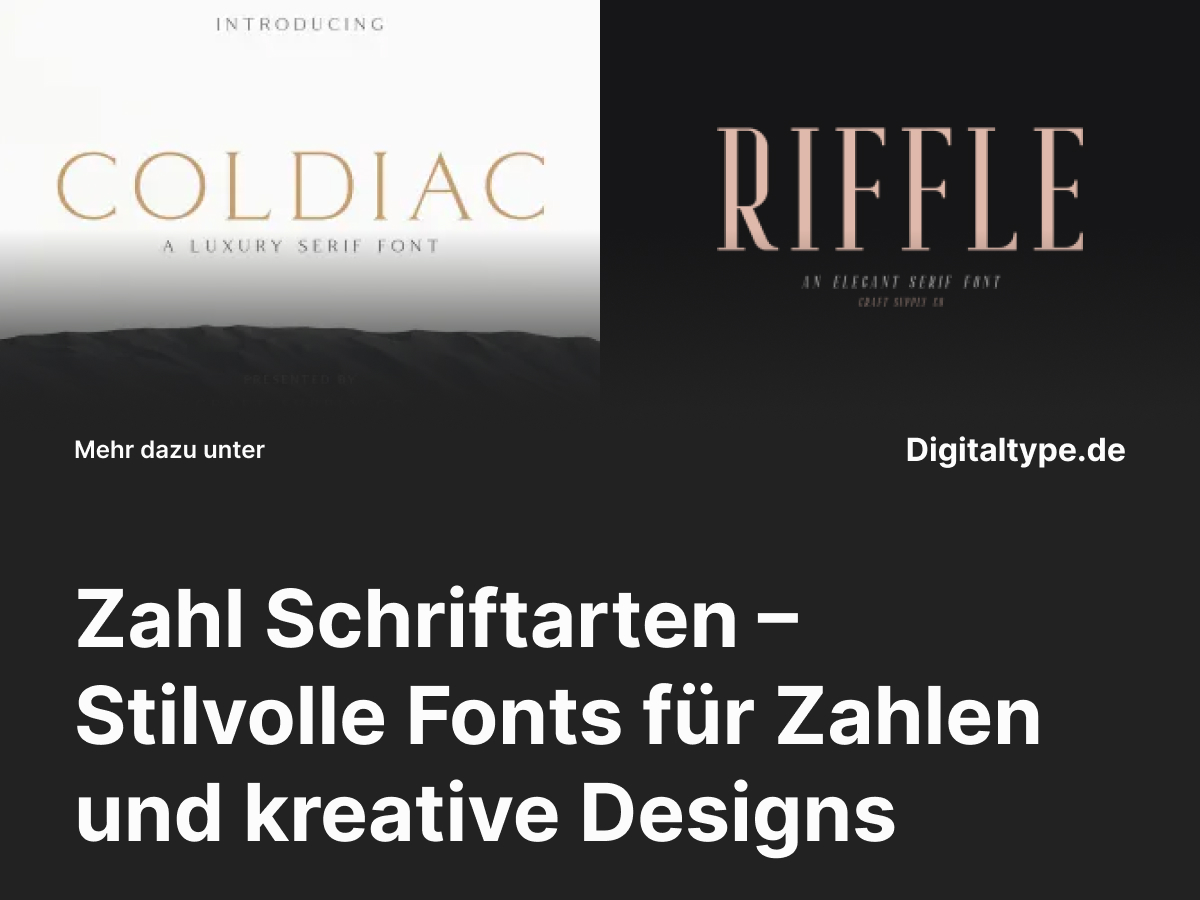
Zahl Schriftarten – Stilvolle Fonts für Zahlen und kreative Designs
Zahl Schriftarten sind die perfekte Wahl, wenn du deinen Zahlen einen besonderen Charakter verleihen möchtest. Ob für Logos, Uhren, Verpackungsdesigns oder kreative Projekte – mit der richtigen Typografie wird jede Zahl zu einem ästhetischen Highlight. In diesem Artikel zeigen wir dir, welche Zahl-Schriftarten besonders beliebt sind und stellen dir sechs exklusive Alternativen vor, die Eleganz und Lesbarkeit perfekt verbinden.
Was sind Zahl-Schriftarten?
Zahl-Schriftarten sind speziell gestaltete Fonts, die den Fokus auf die Darstellung von Ziffern legen. Während viele Standardschriften Zahlen lediglich ergänzen, bieten Zahlfonts harmonische Proportionen, präzise Linien und ein ausgewogenes Schriftbild, das sich ideal für Design, Branding oder Editorial-Arbeiten eignet.
Ob minimalistisch, klassisch oder luxuriös – Zahl-Schriftarten verleihen deinen Designs Struktur und Raffinesse. Besonders in der Markenkommunikation oder auf Produkten mit Nummerierungen können sie einen entscheidenden Unterschied machen.
Wann du Zahl-Schriftarten verwenden solltest
• 1. Für Branding und Logos: Wenn du Zahlen in dein Markendesign integrieren möchtest, etwa Jahreszahlen oder Modellnummern.
• 2. In Editorial-Designs: Für elegante Kapitelnummern, Überschriften oder Preisangaben.
• 3. Auf Verpackungen: Wenn Zahlen Teil des visuellen Konzepts oder Produktnamens sind.
• 4. Für kreative Typografie-Projekte: Ideal, um Schrift und Form zu kombinieren und visuelle Spannung zu erzeugen.
Eine gute Zahl Schriftart sorgt für Wiedererkennbarkeit, Lesbarkeit und einen professionellen Look – egal, ob im Print oder Digitalbereich.
Die 6 besten Zahl-Schriftarten für Design und Branding
Hier findest du eine Auswahl von sechs hochwertigen Zahl Schriftarten, die sich perfekt für professionelle und kreative Anwendungen eignen. Alle Fonts sind modern, klar und stilvoll gestaltet – ideal für Logos, Magazine oder Produktverpackungen.
1. Coldiac Luxury Serif Font
Coldiac steht für Luxus und Eleganz. Diese Serifenschrift eignet sich hervorragend für Designs, die Klasse und Exklusivität ausstrahlen sollen – ideal für Zahlen in Mode-, Schmuck- oder Lifestyle-Brandings.
2. Riffle Font Family
Riffle kombiniert klassische Serifen mit modernen Akzenten. Ihre klaren Ziffern sind perfekt für hochwertige Layouts, Preisangaben oder Kalenderdesigns geeignet.
3. Aguero Serif Clean Elegant Font
Aguero besticht durch ihre feinen Linien und harmonische Struktur. Diese Schrift ist ideal für dezente, aber stilvolle Zahlen – etwa auf Verpackungen, Visitenkarten oder im Editorial-Design.
4. Espoir Serif Font Family
Espoir ist eine elegante Serifenschrift mit klassischer Note. Ihre präzise gestalteten Ziffern machen sie perfekt für Marken, die auf Professionalität und Zeitlosigkeit setzen.
5. Rolves Sans Serif Font Family
Rolves ist modern, minimalistisch und vielseitig einsetzbar. Ihre klaren Zahlen passen perfekt in digitale Projekte, Benutzeroberflächen oder moderne Unternehmensauftritte.
6. Gasolyn Font Family + Extras
Gasolyn bringt Vintage-Flair in moderne Designs. Mit ihren markanten Ziffern ist sie ideal für Retro-Brandings, Poster oder kreative Layouts mit starkem Charakter.
Design-Tipps für Zahl-Schriftarten
• 1. Kontrast ist entscheidend: Wähle eine Schrift, deren Zahlen sich klar vom Hintergrund abheben.
• 2. Achte auf Lesbarkeit: Besonders bei kleinen Größen sollten Ziffern gut unterscheidbar bleiben.
• 3. Kombiniere Serif- und Sans-Serif-Fonts: So entsteht ein spannender visueller Kontrast in deinen Designs.
• 4. Einheitliches Zahlenbild: Verwende für alle Zahlen im Projekt dieselbe Schriftart, um Konsistenz zu schaffen.
Fazit: Zahl Schriftarten – Eleganz und Präzision für deine Designs
Eine Zahl Schriftart ist weit mehr als nur ein Detail – sie ist ein Gestaltungselement, das Struktur, Ästhetik und Markenidentität unterstreicht. Ob für edle Logos, moderne Magazine oder digitale Interfaces – die richtige Typografie hebt dein Design auf ein neues Niveau.
Die hier vorgestellten Fonts bieten dir vielfältige Möglichkeiten, mit Zahl-Schriftarten zu experimentieren und deine Projekte mit Stil und Präzision zu gestalten.